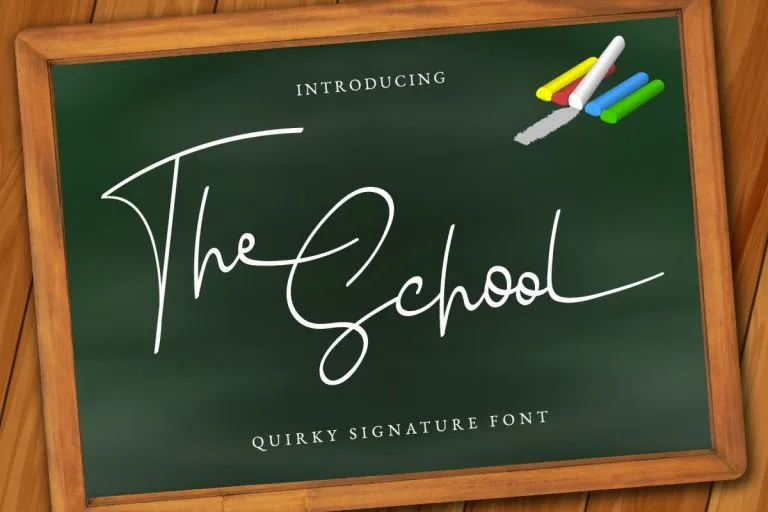
The school Font
A escolha certa para sua próxima criação criativa, a School Font oferece uma assinatura escrita à mão com fluidez natural. Ideal tanto para designers quanto para amantes do estilo manuscrito, essa font elege-se como o script perfeito para diversas aplicações, desde cartas de cumprimentos até as identidades dos seus produtos mais pessoais. Com seu charme quirk, a School Font se destaca não apenas por sua elegância inconfundível, mas também pela versatilidade que proporciona. Suas linhas fluidas e personalizadas permitem um toque único em qualquer projeto – seja um design de card de nome personalizado para clientes ou uma criação de arte digital. A escolha certa para dar um tom encantador a seus projetos, a School Font é mais do que apenas uma fonte, ela é um complemento criativo que enriquece suas ideias e torna seu trabalho ainda mais especial.